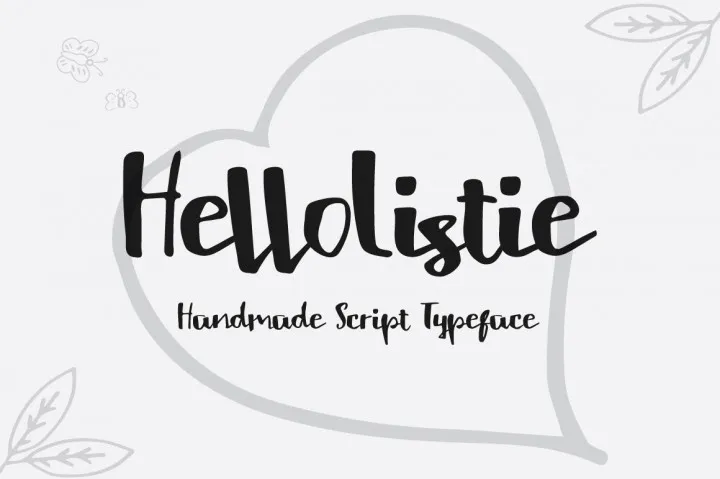
Hello Listie Script Font – Download Grátis
A fonte ‘Hello Listie’ é uma opção premium agora gratuita do site TheHungryJpeg, localizada no arredondado universo dos 43 Fonts gratuitos disponíveis lá. Esta font foi criada pelo designer Hamilton e adicionou um toque de elegância à sua página com apenas alguns cliques. É perfeita para aqueles que desejam dar uma roupagem especial aos seus projetos digitais. Nota-se que esta oferta gratuita é válida por apenas 14 dias, então não perca tempo – se você aprecia esse estilo de fonte elegante e moderna, aproveite agora mesmo a oportunidade de adquiri-la para uso pessoal ou profissional.